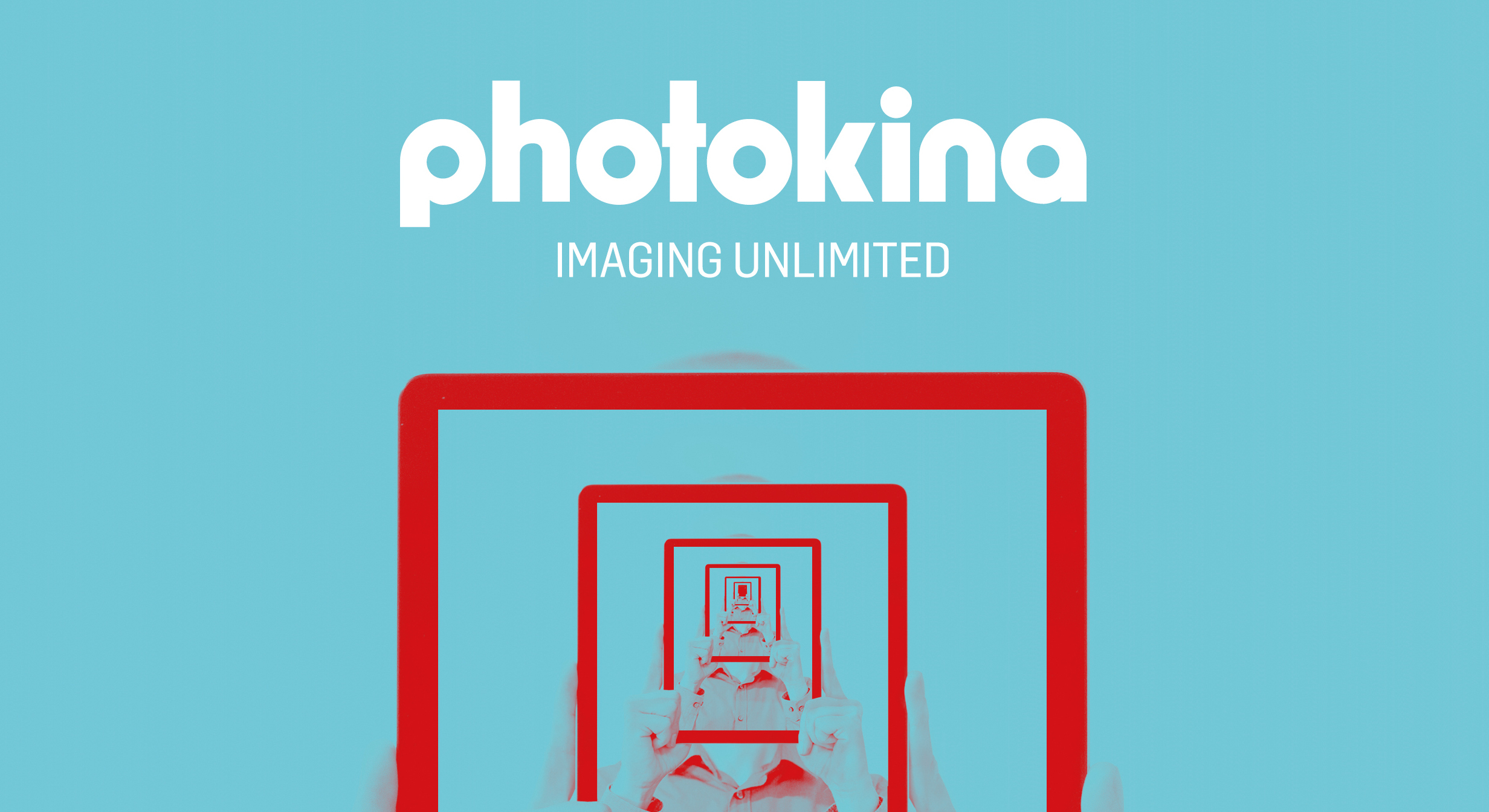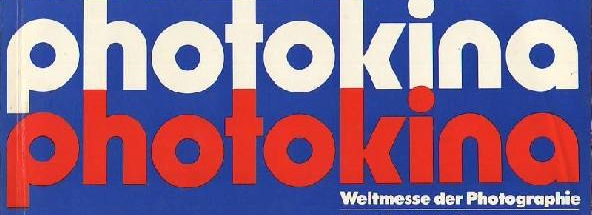
Logo der Photokina
Hallo, mich würde interessieren um welche zwei Schriftarten es sich beim Titel der Photokina 2016 handelt. Handelt es sich bei der Headline lediglich um ein Logo oder um einen bereits bestehenden Font? Oder ist es eine  "customized Typo"?
Wenn ich mir die Geschichte des Logos (Abb. v. 1970 und 1980) so anschaue, dann basiert es wahrscheilich auf einer Futura, die im Laufe der Zeit abgerundet wurde, und damit eher wie die Bauhaus, Blippo oder Pump wirkt. Ähnliche dazu hier.